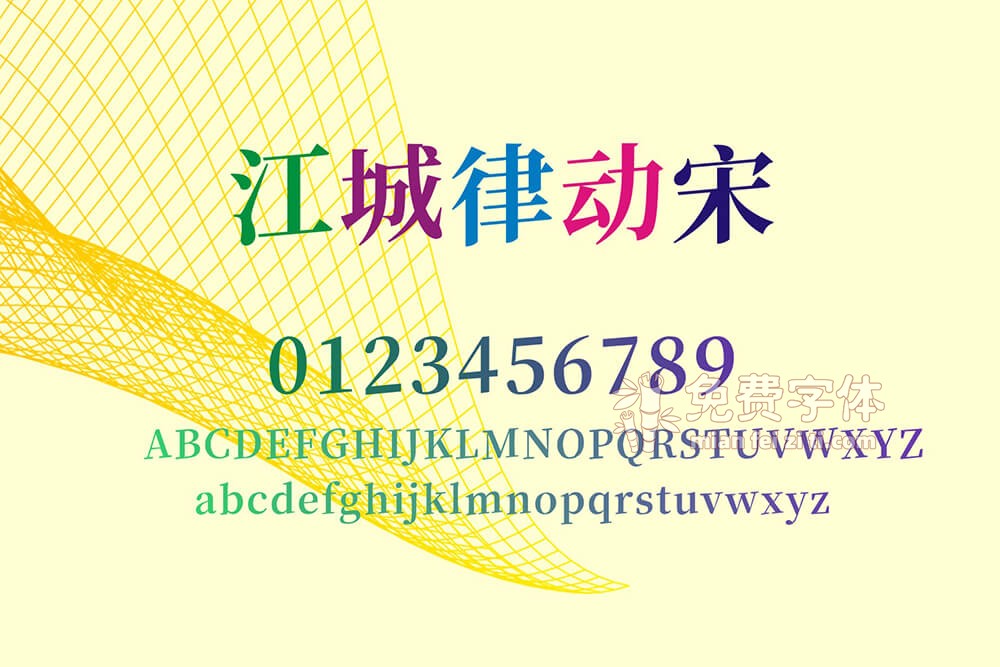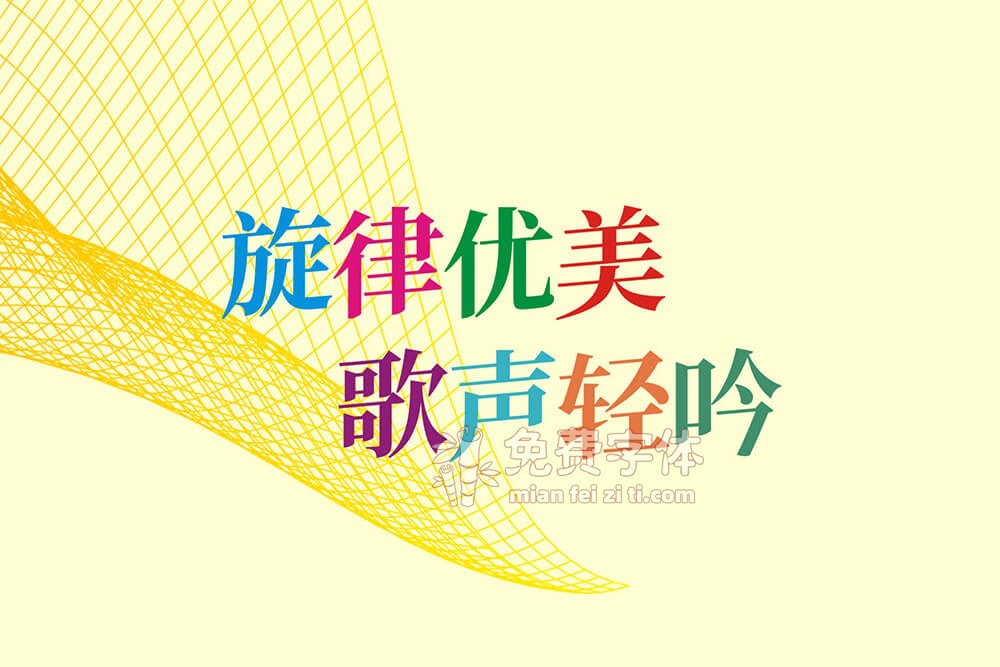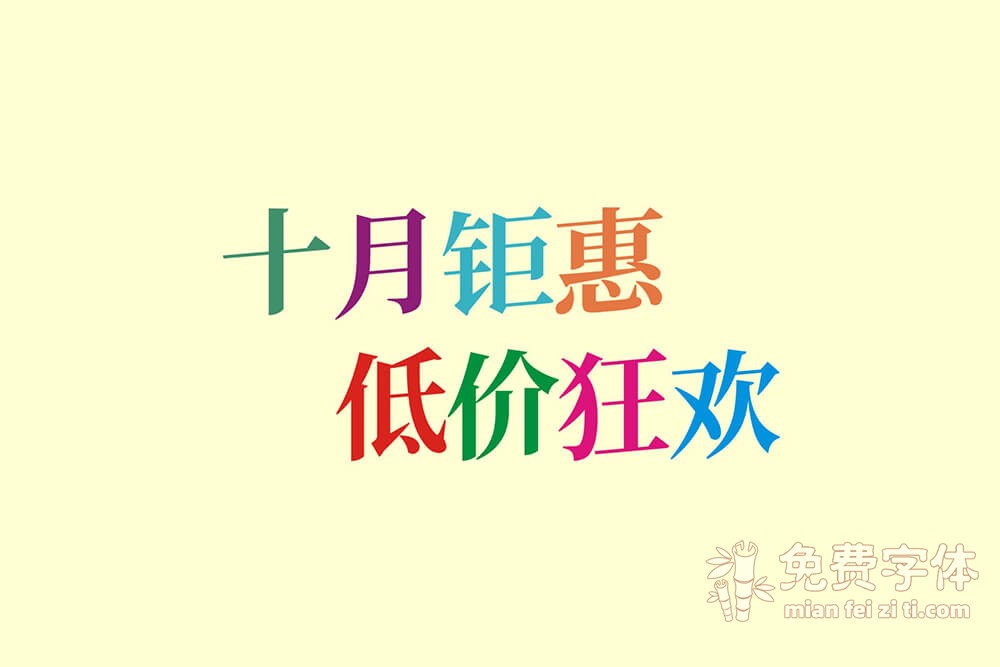
江城律动宋是大神@刘鹏基于思源宋体CN-Bold向上倾斜5度改造的一款字体。江城律动宋字体向上倾斜,上下律动,自带活动促销BGM,天生适用于活动、促销等广告语,适当缩小字间距效果更佳哦。
把字体向上倾斜,让字体有了一种动感。江城律动宋与猫啃网风雅宋的不同之处在于,两款字体向上倾斜的角度不一样,江城律动宋的倾斜度会更高一点